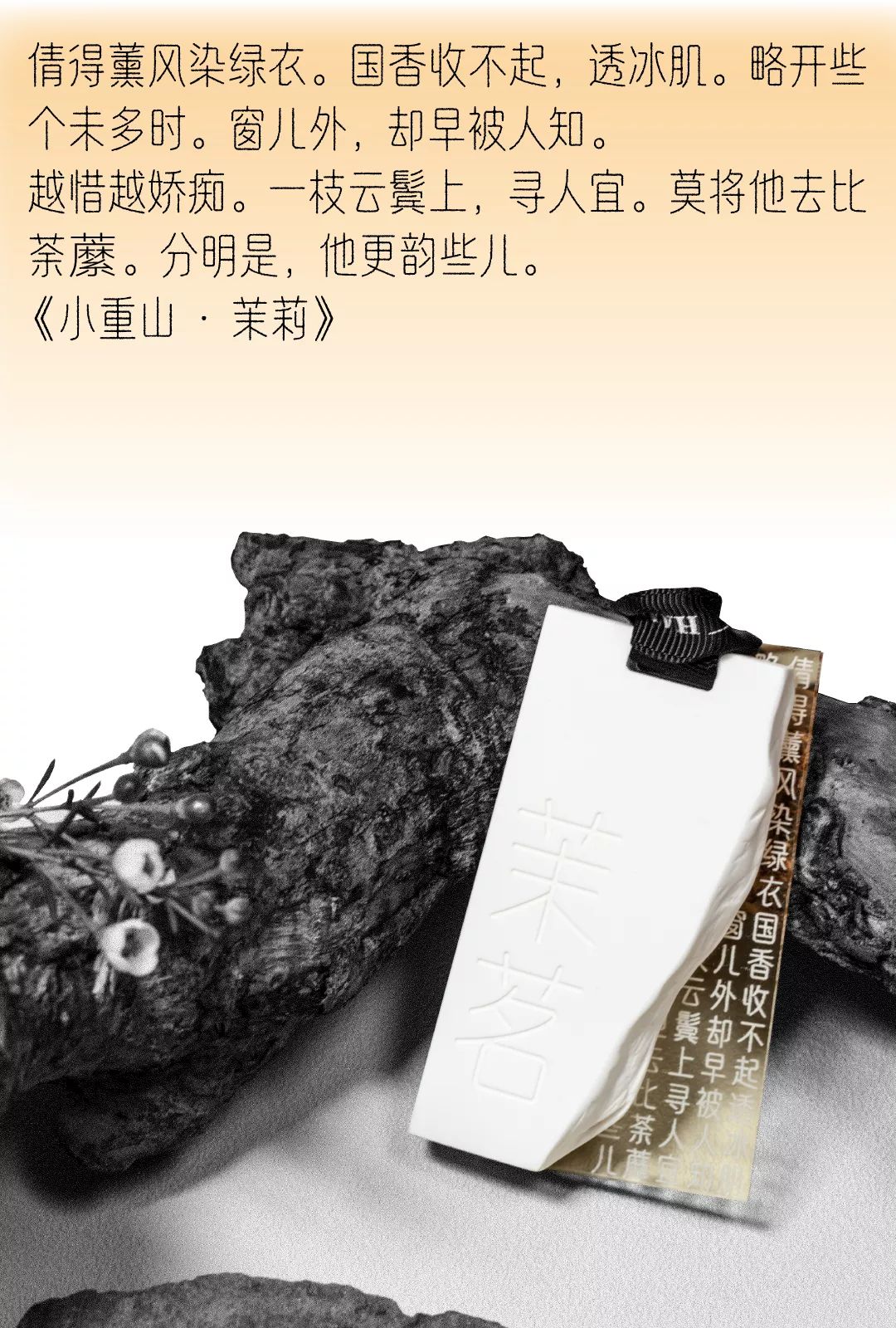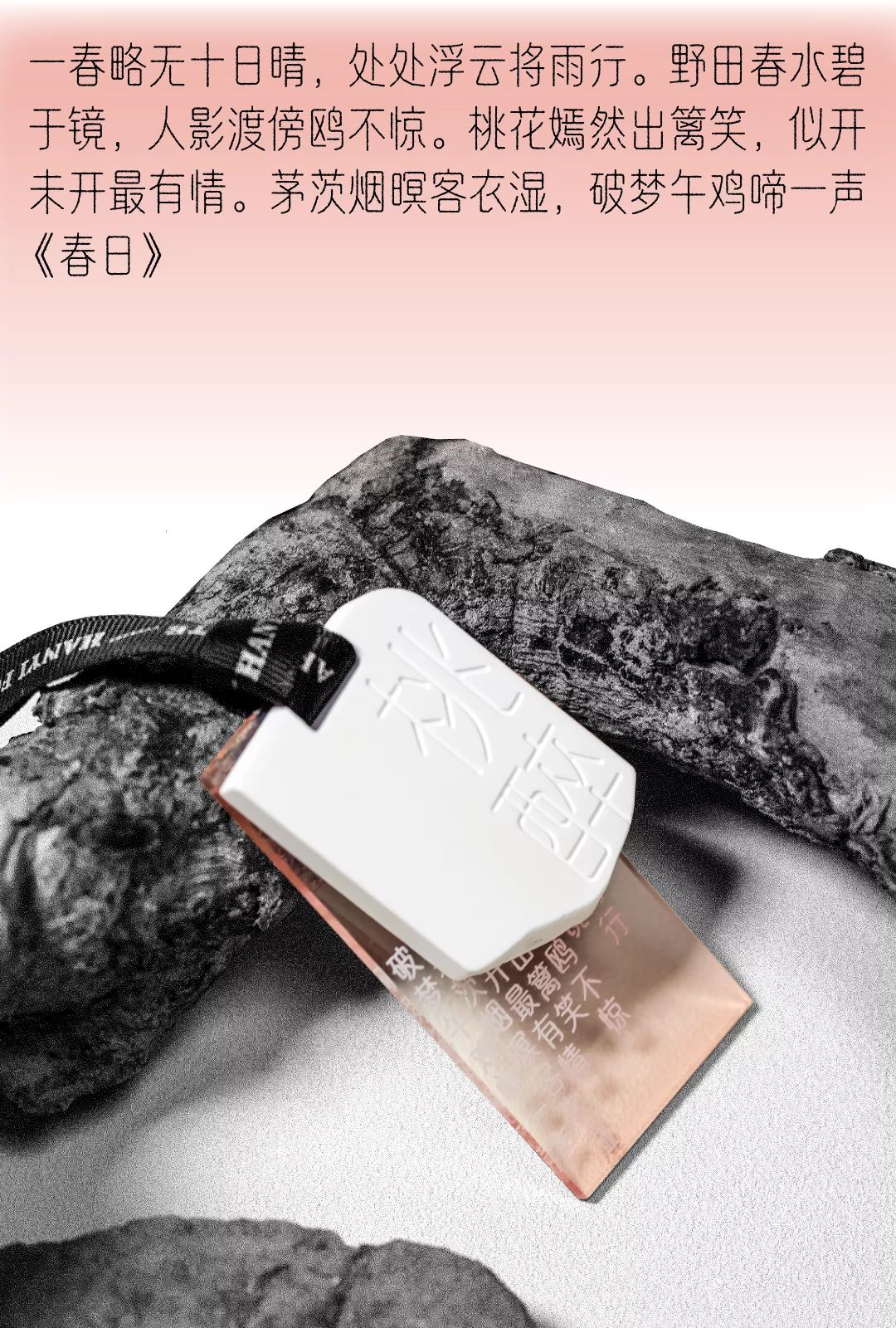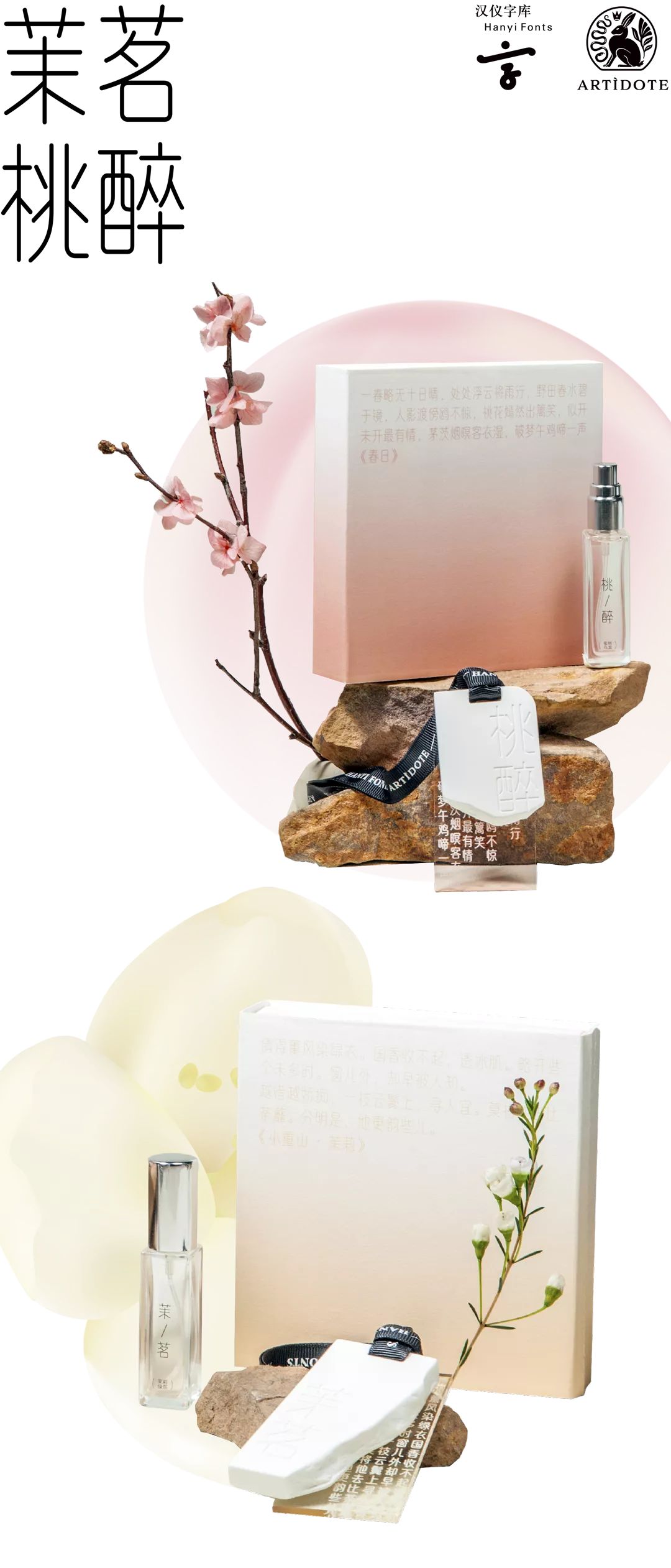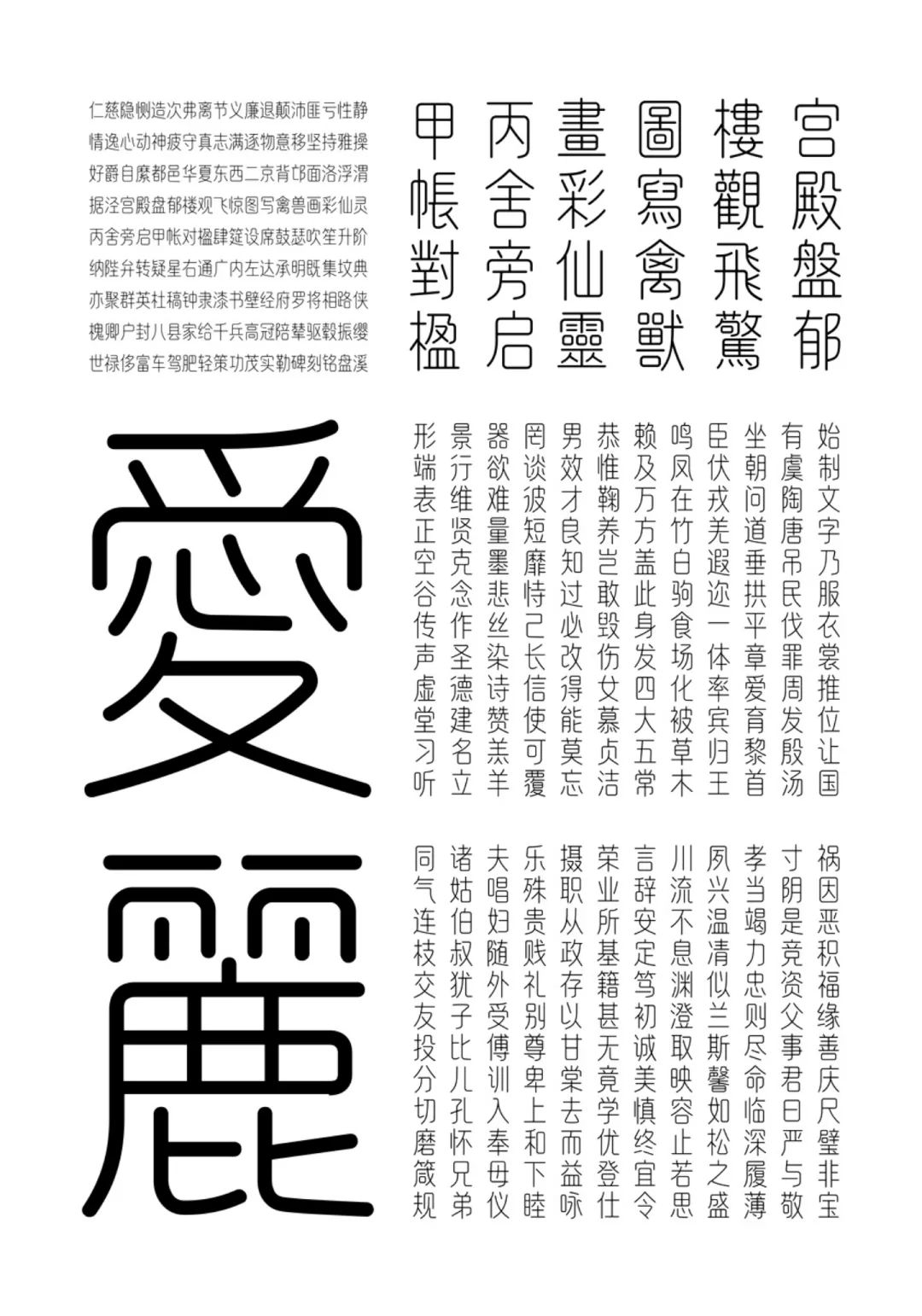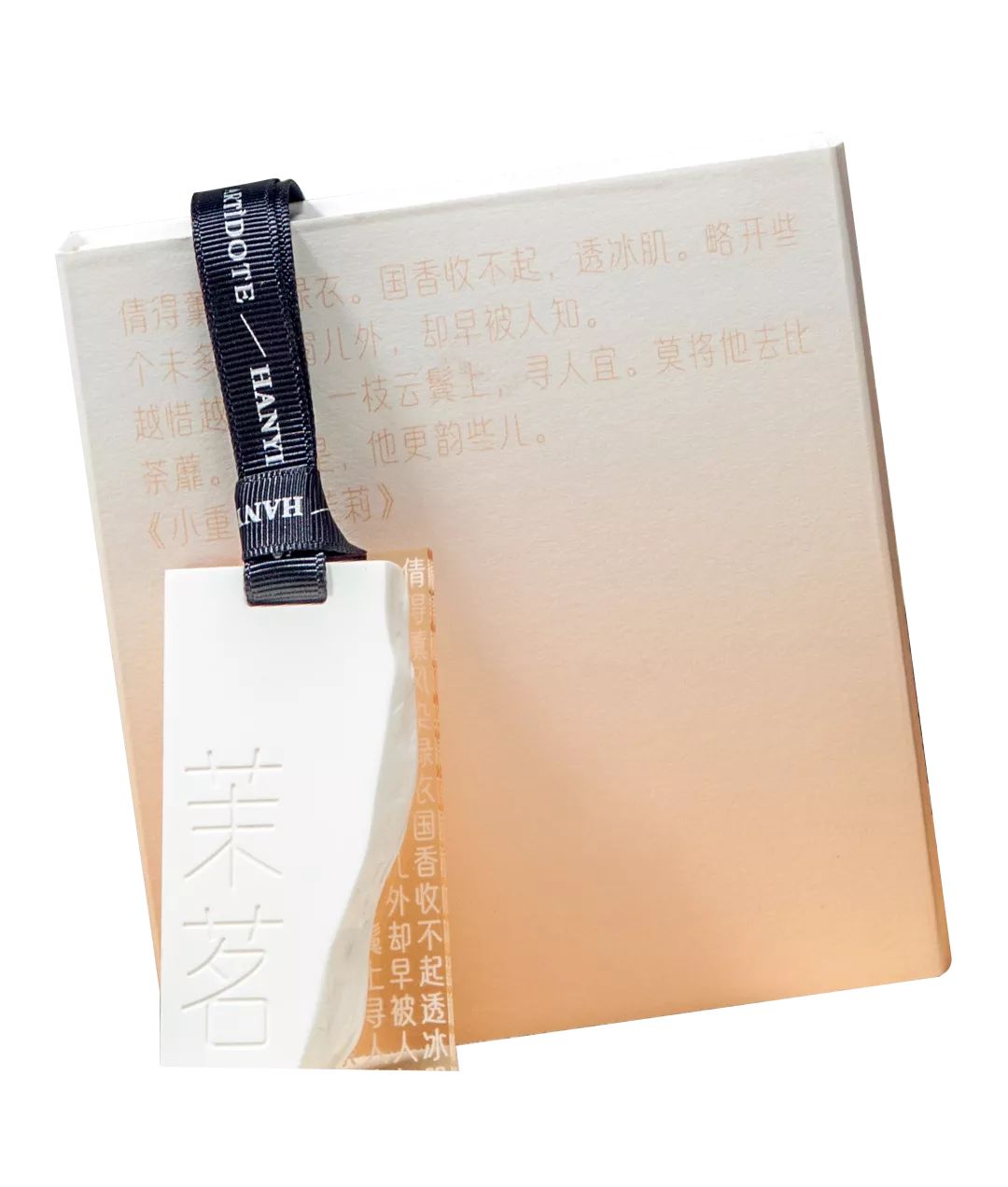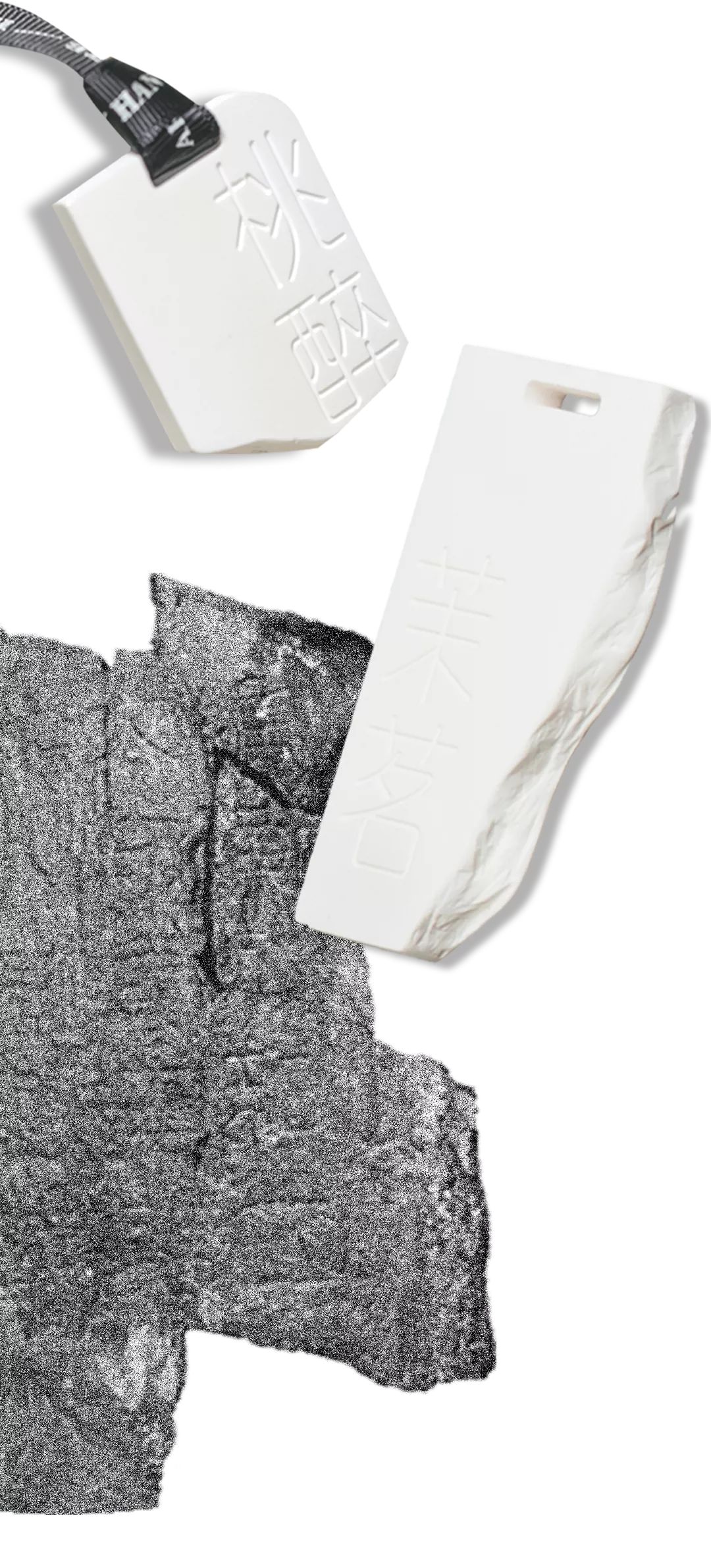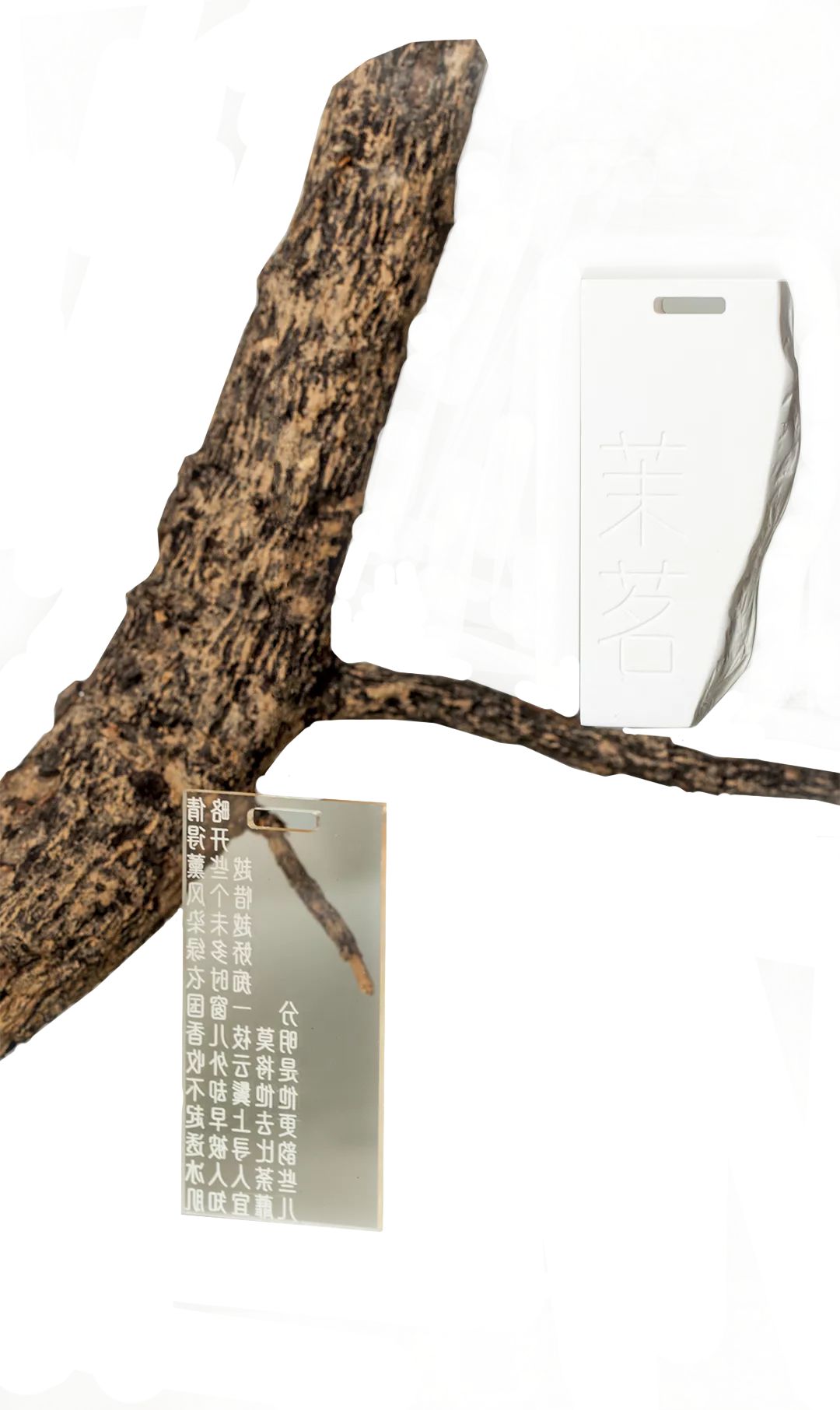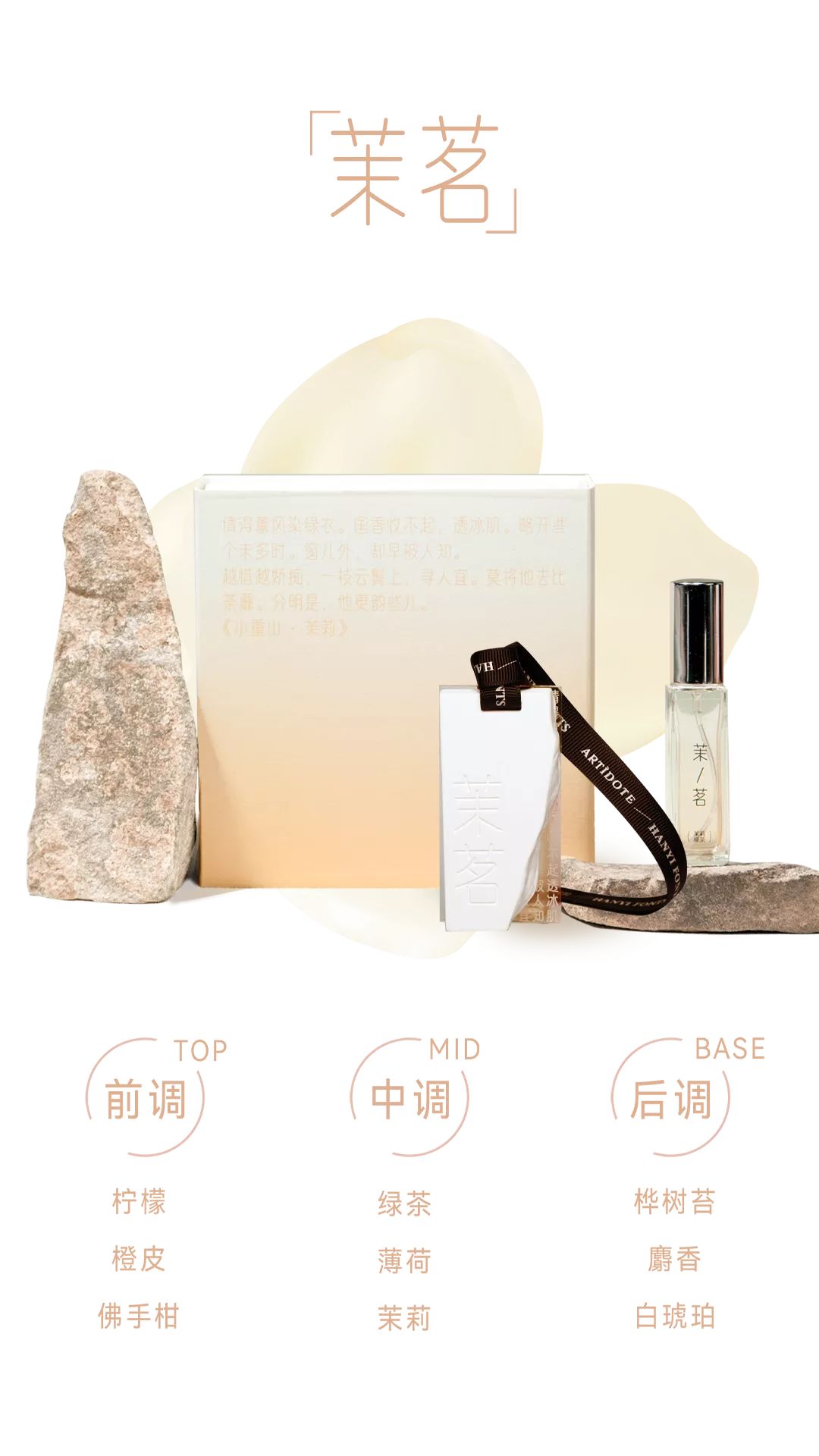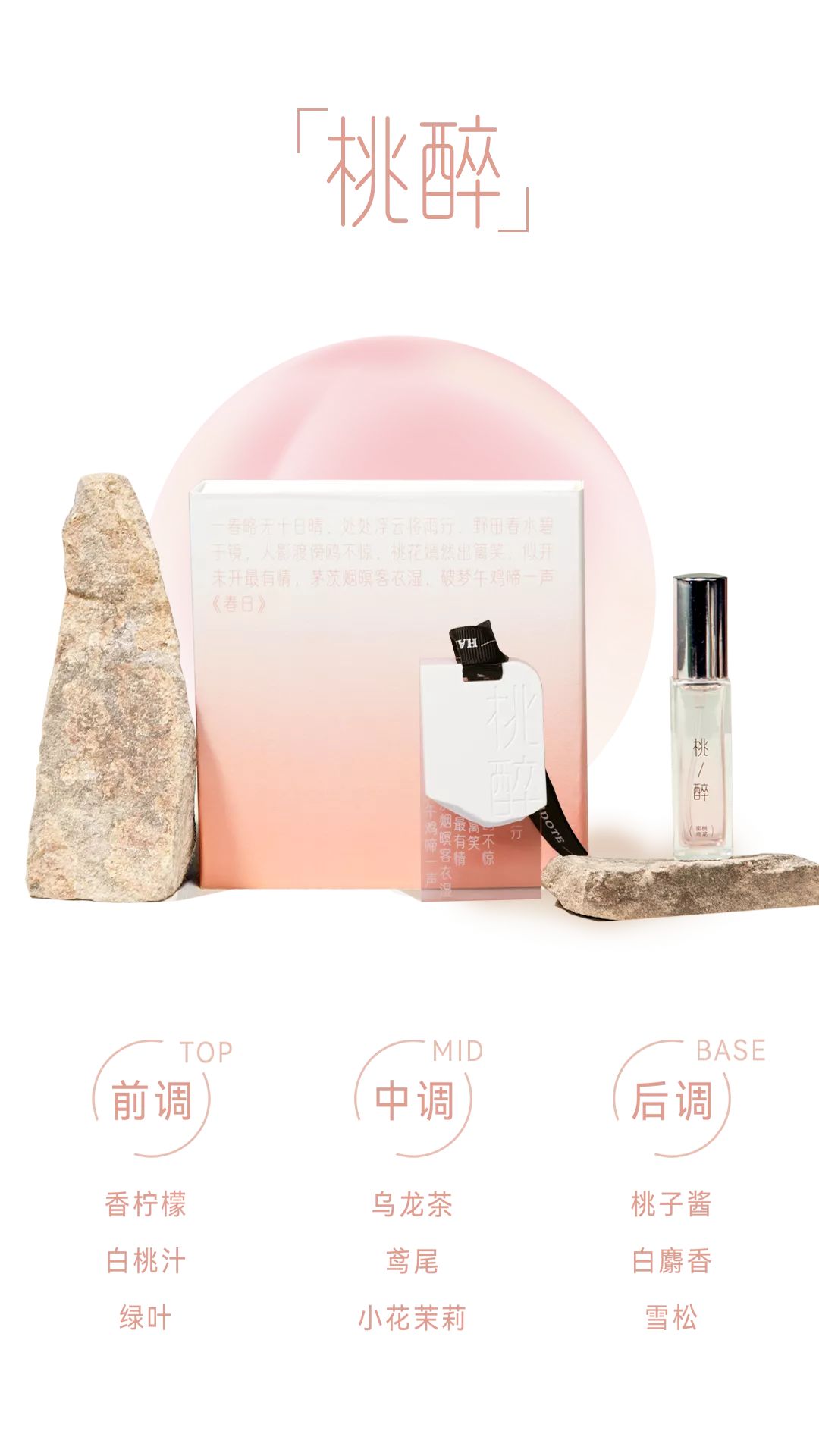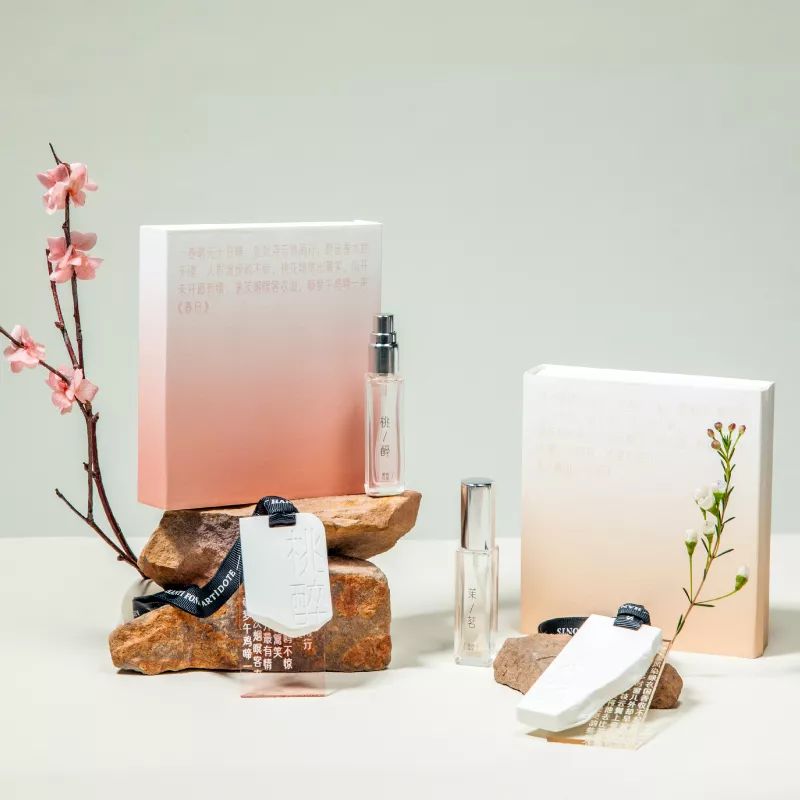
茉茗桃醉的诗意汉字
东方美学讲究意境,
意境之情在于言外,
心中有、口中无,模糊朦胧,若隐若现。
汉仪字库联合香薰品牌ARTÌDOTE
从古诗词找寻灵感
创作了两款香薰挂件
字里行间,营造东方诗意
汉字灵感:汉仪天诺丽线
汉仪天诺丽线是这款香牌所使用的字体,字形高挑,线条洁净,兼具古韵与现代。
在整个包装与产品的设计开发中,汉仪天诺丽线不仅仅作为承载信息的载体,更是通过自身与众不同的气质,由内而外尽显东方美。
造型灵感:碑刻
香牌的造型灵感源自汉仪天诺丽线原碑(敦煌太守裴岑纪功碑),独特的不规则轮廓模拟因岁月打磨而产生的变化,是经历时间考验的不完美之美。
材质灵感:石膏×亚克力
选用两种不同的“石头”材质,交错重叠,形成更为丰富的层次感。悬挂后,石膏与亚克力,将翱将翔,佩玉将将。
气味灵感:温灯饮茶,无事熏香
茉茗 | 茉莉绿茶:“他年我若修花史,列作人间第一香”,茉莉与绿茶的结合,仿若一盏茶汤,沁人心脾,鲜灵持久。
桃醉 | 蜜桃乌龙 :水蜜桃成熟后的诱人香甜与乌龙茶入口后的醉人甘甜,相得益彰,前者青春洋溢,后者高雅浓醇。
汉字的另一种打开方式:
风云吐於行间,珠玉生於字里。当汉字不再只是传播信息的工具,从文字到文化再到文创,我们希望通过一份礼物,为你展开一段有温度的故事。放逐感官,尽情享受文汉字带来的东方诗意旅程!